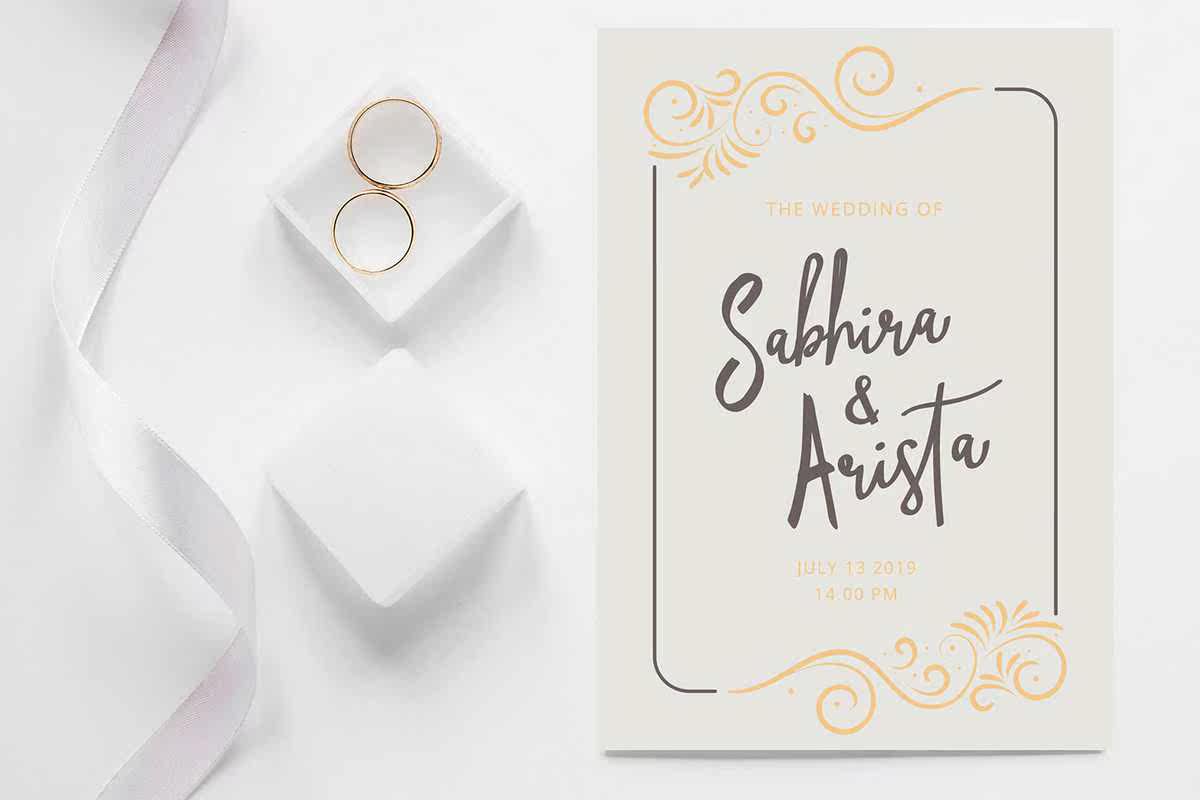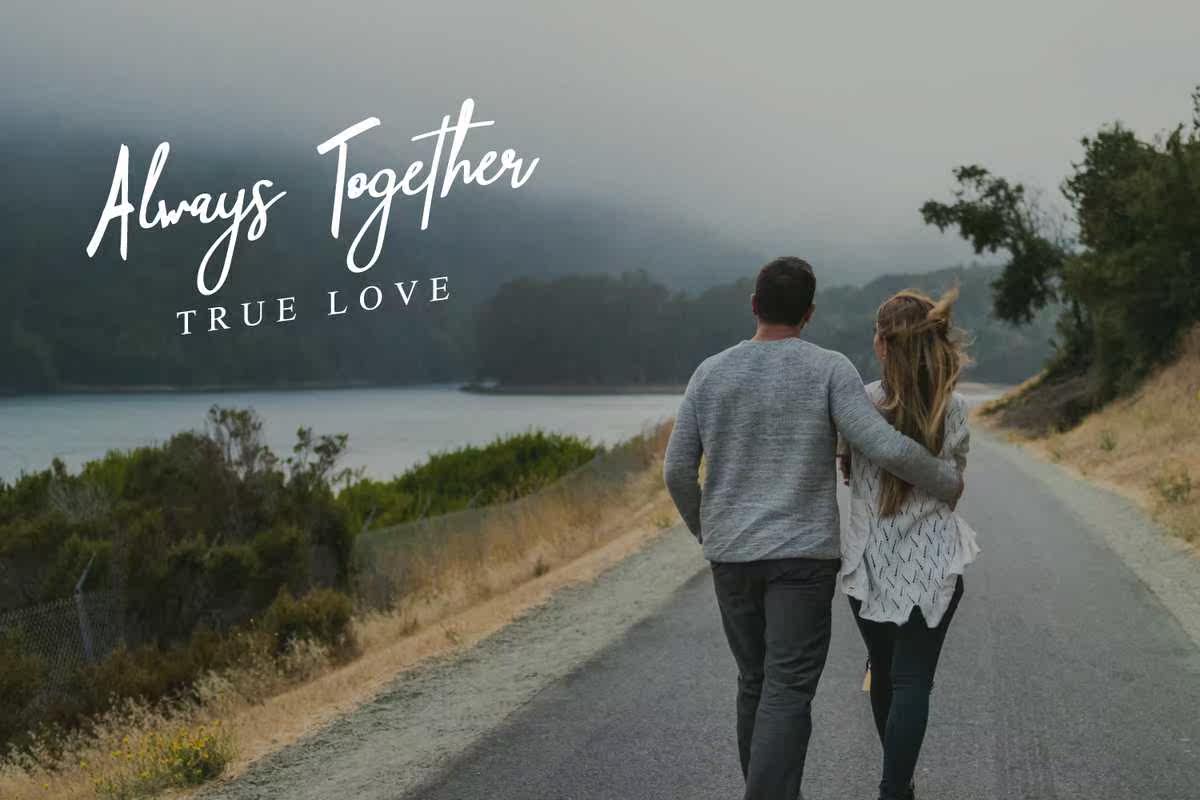
Kaydenisabeautifula和CoolHandwritenFont,FeatureingAlvelyStyle。Nomatterthetopic,此Font将无法可靠地访问您的字体库,因为它是提升任何创作的潜在工具。Kaydenisabeautifula和CoolHandwritenFont,FeatureingAlvelyStyle。Nomatterthetopic,此Font将无法可靠地访问您的字体库,因为它是提升任何创作的潜在工具。